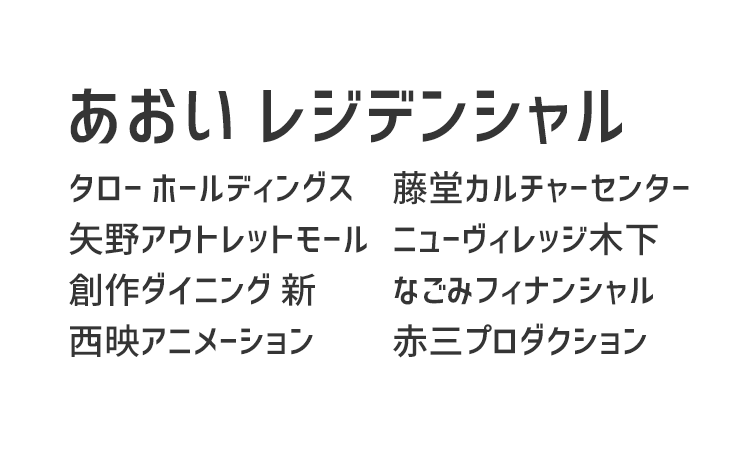
コーポレート・ロゴは、企業サイトのロゴでの使用にオススメのゴシック体フォントです。企業やサービスに使われるような、モダンでシンプルなロゴ文字に仕上がっています。洗練されたデザインで、そのままロゴとして使うこともできます。文字としての可読性は残しながら、それぞれの文字が持っている特徴を極限まで削ぎ落としてあります。余計な装飾のない自然な形状で、信頼感や安心感を与えることができます。ボールド体とミディアム体、2つのウェイトが用意されています。
コーポレート・ロゴ Bold
コーポレート・ロゴ Medium